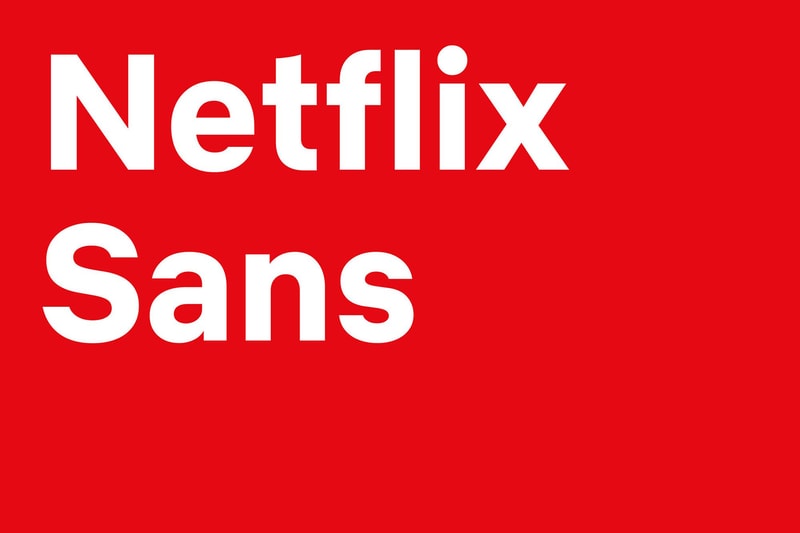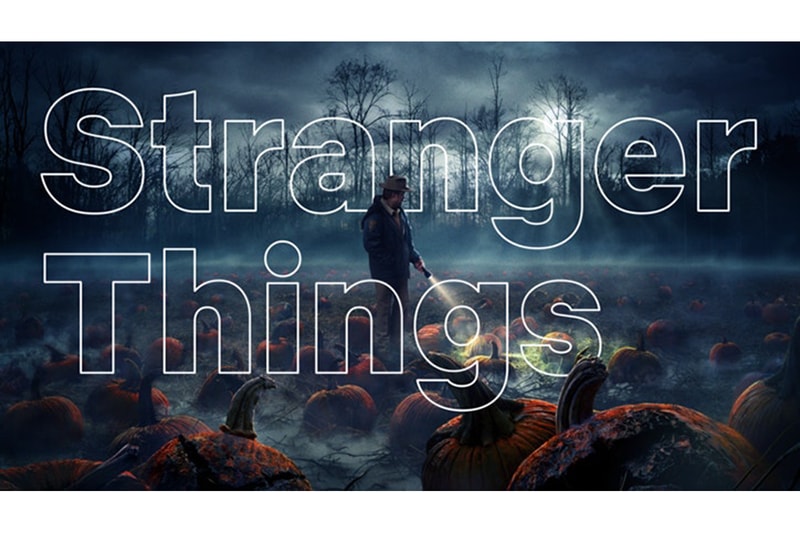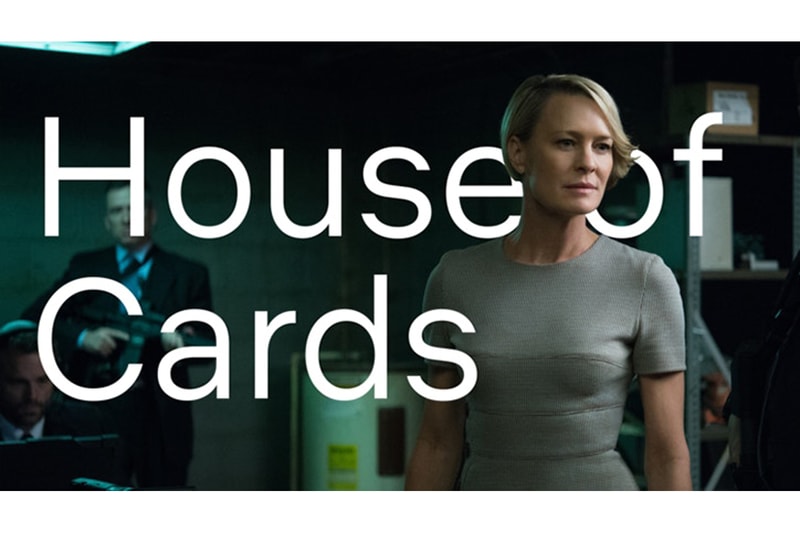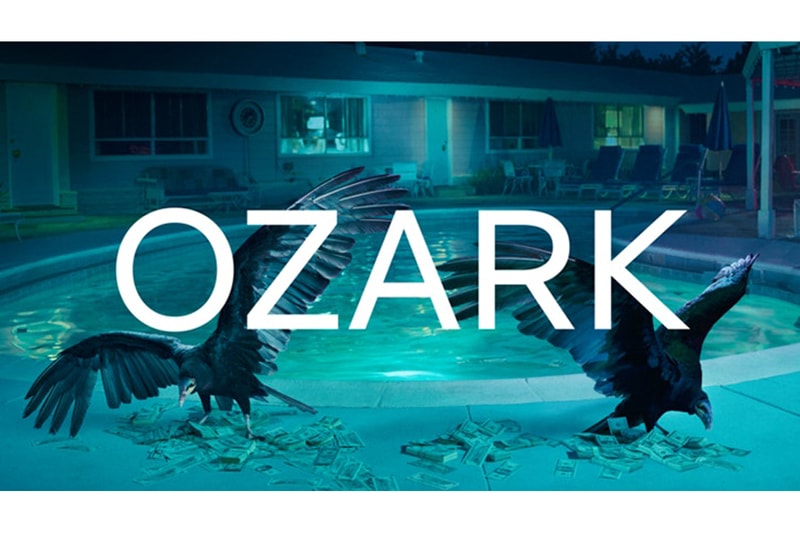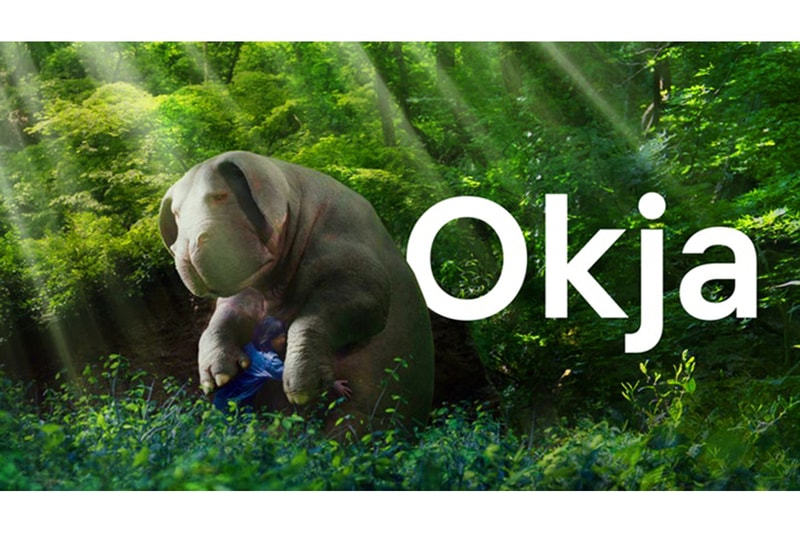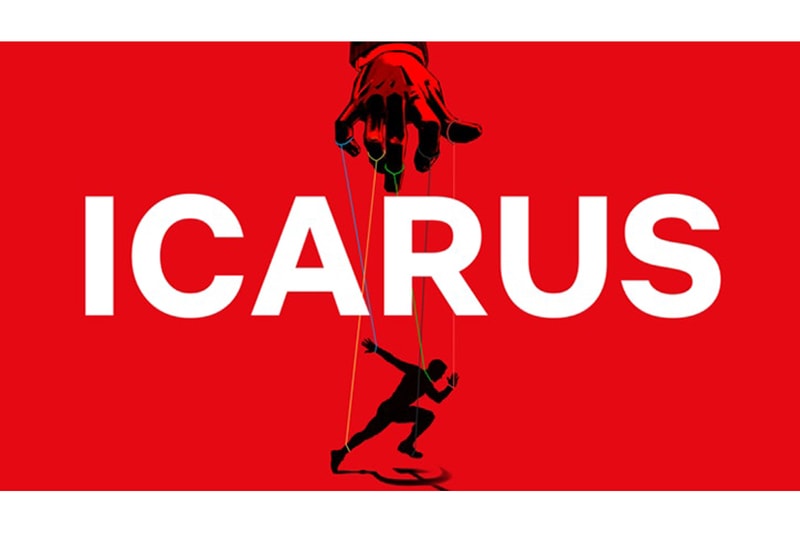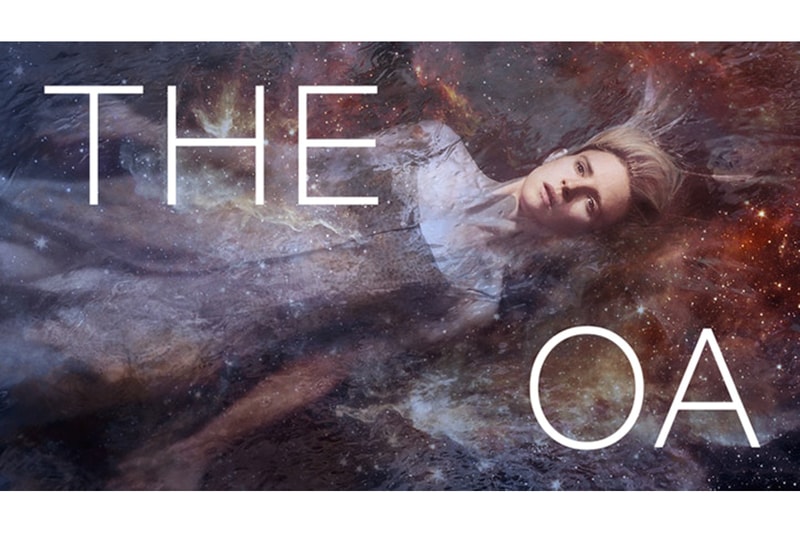
넷플릭스가 인하우스 폰트를 론칭하는 뜻밖의 이유
‘Netflix Sans’.
넷플릭스가 서비스에 사용되고 있는 폰트를 전면 변경한다. <It’s Nice That>에 따르면 기존의 고담(Gotham) 활자체는 런던 기반 디자이너 달튼 맥이 개발한 ‘넷플릭스 산스(Netflix Sans)’로 대체된다. 서체의 사용권 비용이 점점 증가한 것이 그 이유. 고담 폰트의 사용료는 1년에 무려 백만 불 이상이다. 이번 변경에 대하여 넷플릭스의 수석 디자이너 노아 네이선은 비용 절감과 새로운 브랜드 미학을 위해 이 같은 결정을 했다고 밝혔다. 이로 인해 넷플릭스 측은 보다 독립적이고 유연한 시스템을 구현할 수 있을 것으로 예측된다. 새롭게 바뀐 넷플릭스를 위에서 확인해보자.